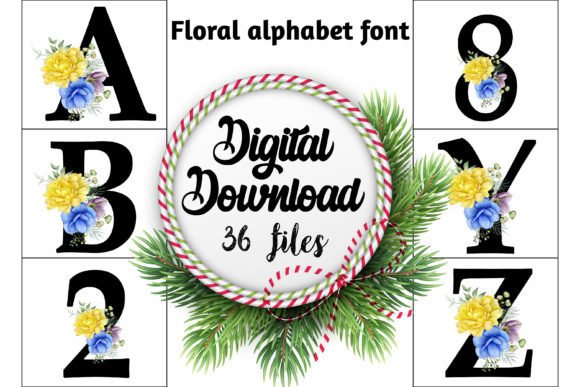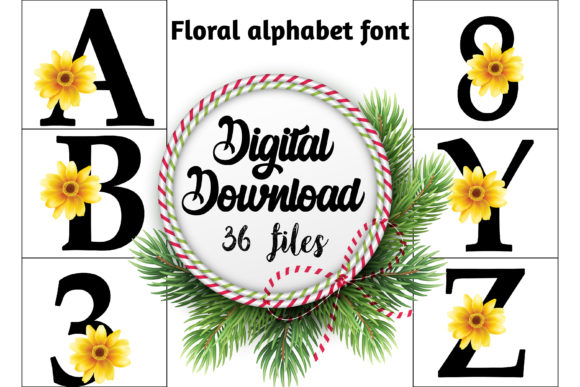
Floral Alphabet Font Set
適切なデザイン要素を見つけるのは難しい場合がありますが、Floral Alphabet Font Setは作品を即座に引き立てる優れたコレクションを提供します。
POD(オンデマンド印刷)製品、結婚式の招待状、またはソーシャルメディアのグラフィックを作成している場合でも、Floral Alphabet Font Setは理想的です。